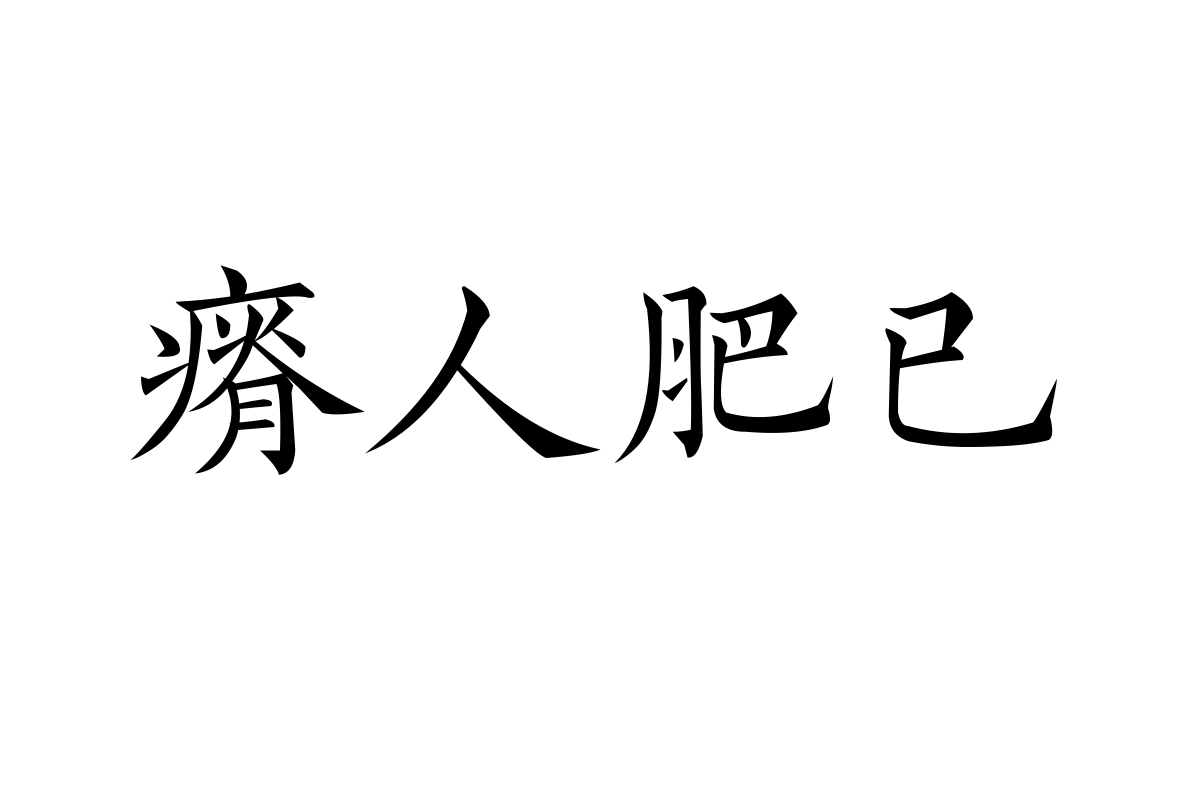
汉仪字酷堂义山楷是一种具有独特风格的书法字体,它源自中国唐代诗人杜牧的《秋夕》一诗中的“义山”二字。这种字体以其独特的结构和笔画特点而闻名,给人一种古朴、典雅的感觉。
汉仪字酷堂义山楷的笔画粗细变化较大,线条流畅且富有弹性。它的结构紧凑,笔画之间相互呼应,形成了一种独特的视觉效果。这种字体适合用于标题、正文等多种场合,能够展现出一种庄重、典雅的气质。